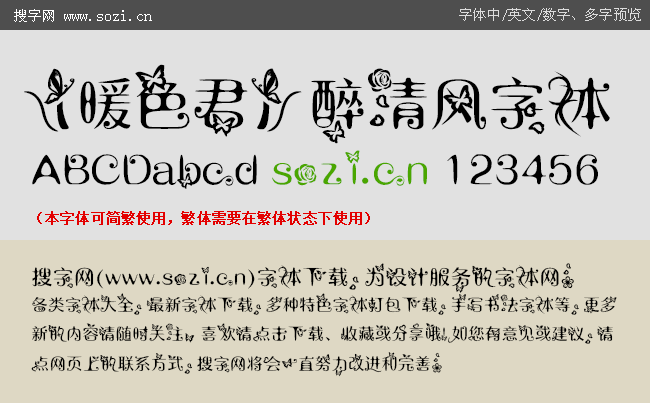
醉清風(fēng)字體
搜字網(wǎng)給大家提供一款有趣的手機(jī)中文字體下載。名為醉清風(fēng)字體,這款手機(jī)中文字體以藝術(shù)字體為原形,字體筆畫(huà)間嵌入了大量的卡通圖案,變成了一款十分卡通的POP藝術(shù)字體,非常適合喜歡個(gè)性的朋友在手機(jī)上安裝使用。